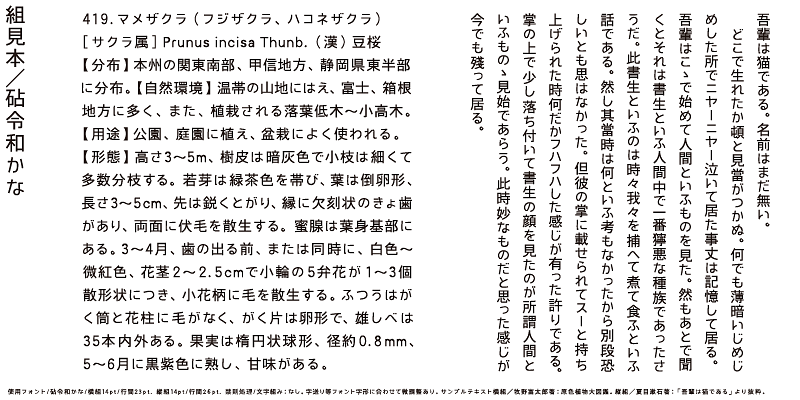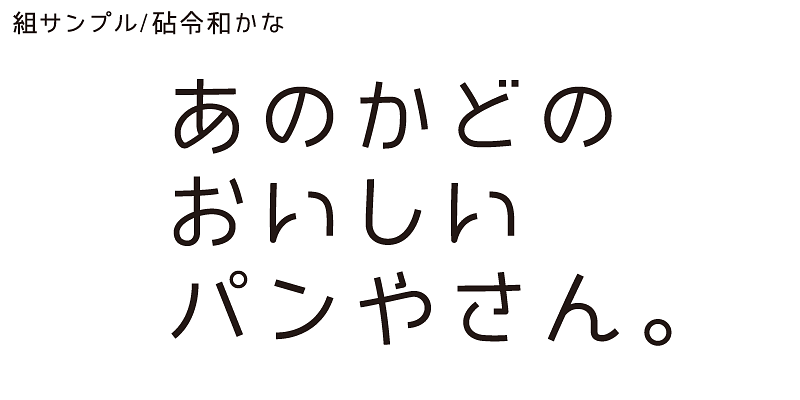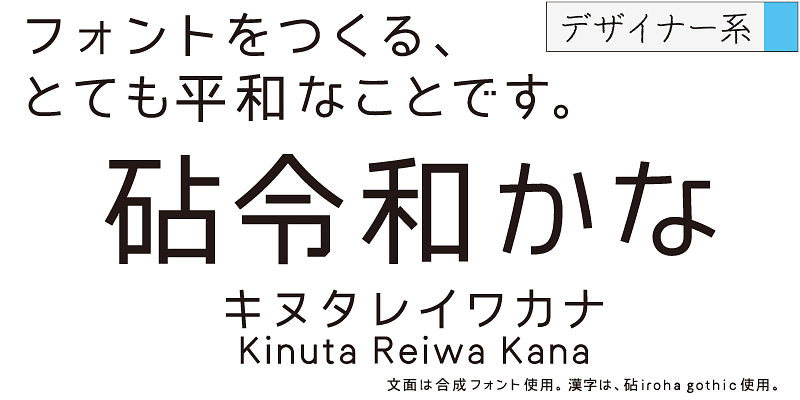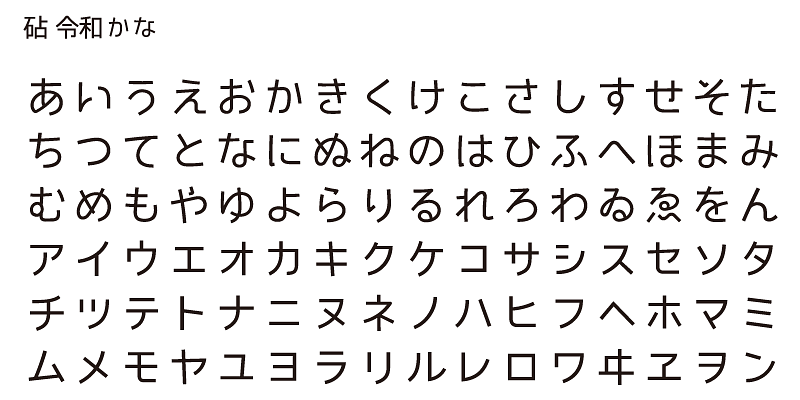
Combinando Reiwa Kana con un carattere tipografico completo in stile gotico, puoi rendere il tuo testo moderno e affascinante. Ti consigliamo di utilizzare iroha come font kanji corrispondente.
Una caratteristica della lingua giapponese è che ha i caratteri sillabici kana. I caratteri Kana furono inventati in Giappone per rappresentare i suoni in giapponese e tradurre in giapponese i testi importati dalla Cina. I caratteri Kana sono necessari per creare parole ed espressioni giapponesi da caratteri ideografici kanji/cinesi. Sebbene possano esserci ambiguità, queste parole ed espressioni mostrano il calore e la dolcezza della vita delle persone che vivono nella piccola e densamente popolata terra del Giappone.
Kinuta Font Factory ritiene che i caratteri kana siano l’origine delle parole scritte in giapponese e riteniamo che il miglioramento dei caratteri kana renderà il testo giapponese più attraente. In media, il 60% del testo giapponese è costituito da caratteri kana: la modifica della forma di questi caratteri modifica l’aspetto visivo del testo. Le possibilità di espressione tipografica utilizzando caratteri kana semplici, dinamici e curvilinei sono vaste e la ricchezza del testo giapponese dipende dai caratteri kana. Questo è il motivo per cui Kinuta Font Factory offre molte varianti di font kana.